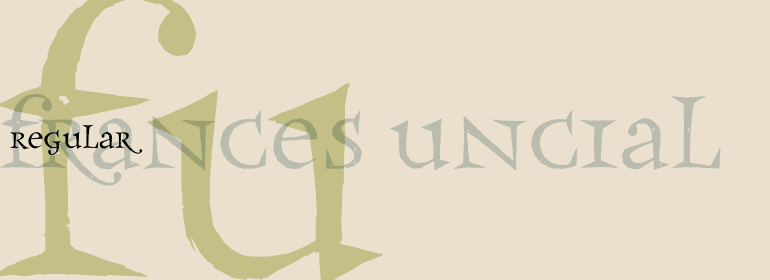
Frances™ Uncial
Frances™ Uncial,这款字体结构工整、笔画清晰,兼顾美观与易读性,适用于标题、正文、海报、包装、LOGO 等多种场景。字形优雅稳定,风格百搭耐看,适配日常排版与创意设计,让文字呈现更舒适、更具质感。Frances™ Uncial一笔一画,皆是细节,以均衡的比例、流畅的线条打造舒适视觉体验,字形端正大气,风格简约现代。无论是商业设计、品牌宣传还是日常排版,都能轻松驾驭,让文字更有格调与力量。Frances™ Uncial字体下载。
Frances Uncial是Michael Gills的作品,他在将字体扫描成数字格式之前,先对字体进行雕刻,从而赋予了字体强烈的触感。结果就创作出一款迷人的古色古香风格的字体。Frances Uncial字体粗糙的边缘使其在较大的字号时非常突出,但在较小的字号时仍然可以保持易读性。
Frances Uncial is the work of Michael Gills, who gave the font a strong tactile appearance by lino-cutting the forms before scanning them into digital form. The result is a captivating typeface with classic, antique-looking forms. The rough edges of Frances Uncial font are best highlighted in larger point sizes yet its legibility is retained in smaller sizes.